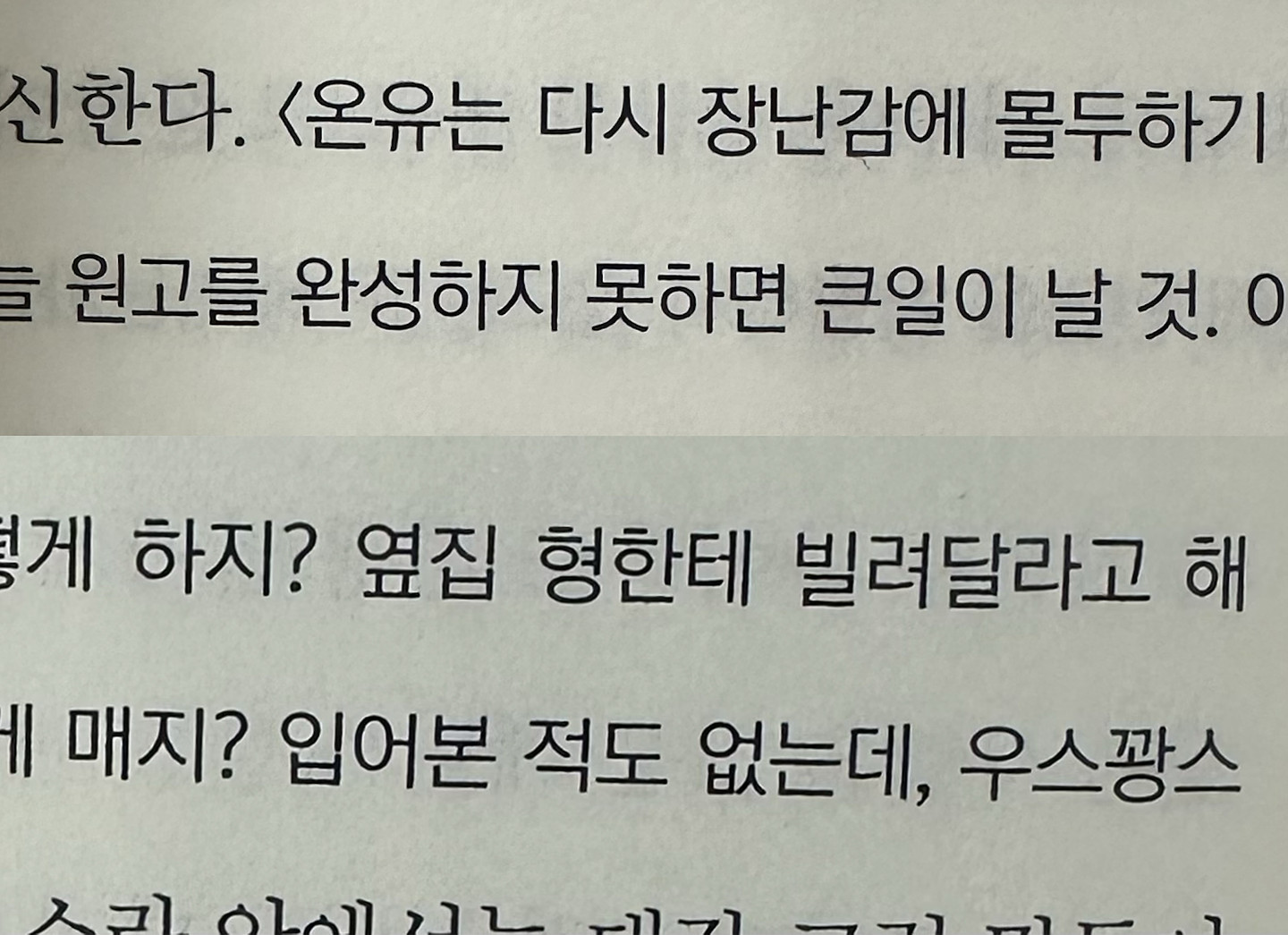
이거 무슨 서체일까요? 'ㅠ'에서 아래를 향하는 왼쪽 획이 곡선져 있는 것이 가장 큰 특징이고 '달, 날'에서 'ㄷ, ㄹ'의 가장 아래 획도 곡선져 있습니다. 이미지 검색으로도 나오지 않아 질문드립니다.ㅜㅜ
안녕하세요 폰트가 너무 이뻐서 질문드립니다 혹시 이 폰트가 뭔지 알 수 있을까요? 아니면 비슷한 폰트라도 추천 받을 수 있을까요?